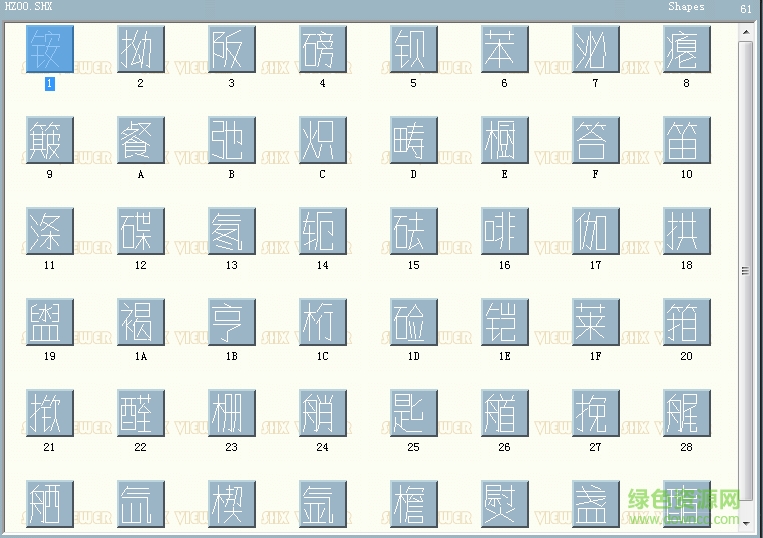
hz00.shx字體是一款autocad的字體文件,線條纖細(xì),字形干凈,安裝該hz00.shx可以幫助用戶更加方便地查看圖紙,有需要者快來綠色資源網(wǎng)下載吧!
hz00.shx字體,這個(gè)字體是auto CAD軟件的大字體,在打開CAD圖紙的時(shí)候,有時(shí)會(huì)提示需要這種hz00.shx字體的選擇,如果沒有這個(gè)hz00.shx大字體的支持,那打開的DWG圖紙里的文字就會(huì)出現(xiàn)問號(hào)。